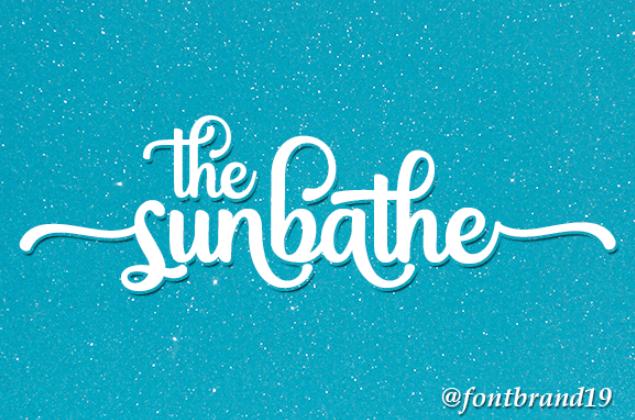
[Creativefabrica] The Sunbathe Font (fontbrand19)
The Sunbathe - красивый и нежный шрифт, излучающий элегантность и класс. Он был специально создан для тех, кому нужен красивый и освежающий вид. Этот шрифт имеет кодировку PUA, что означает, что вы можете легко получить доступ ко всем удивительным глифам.